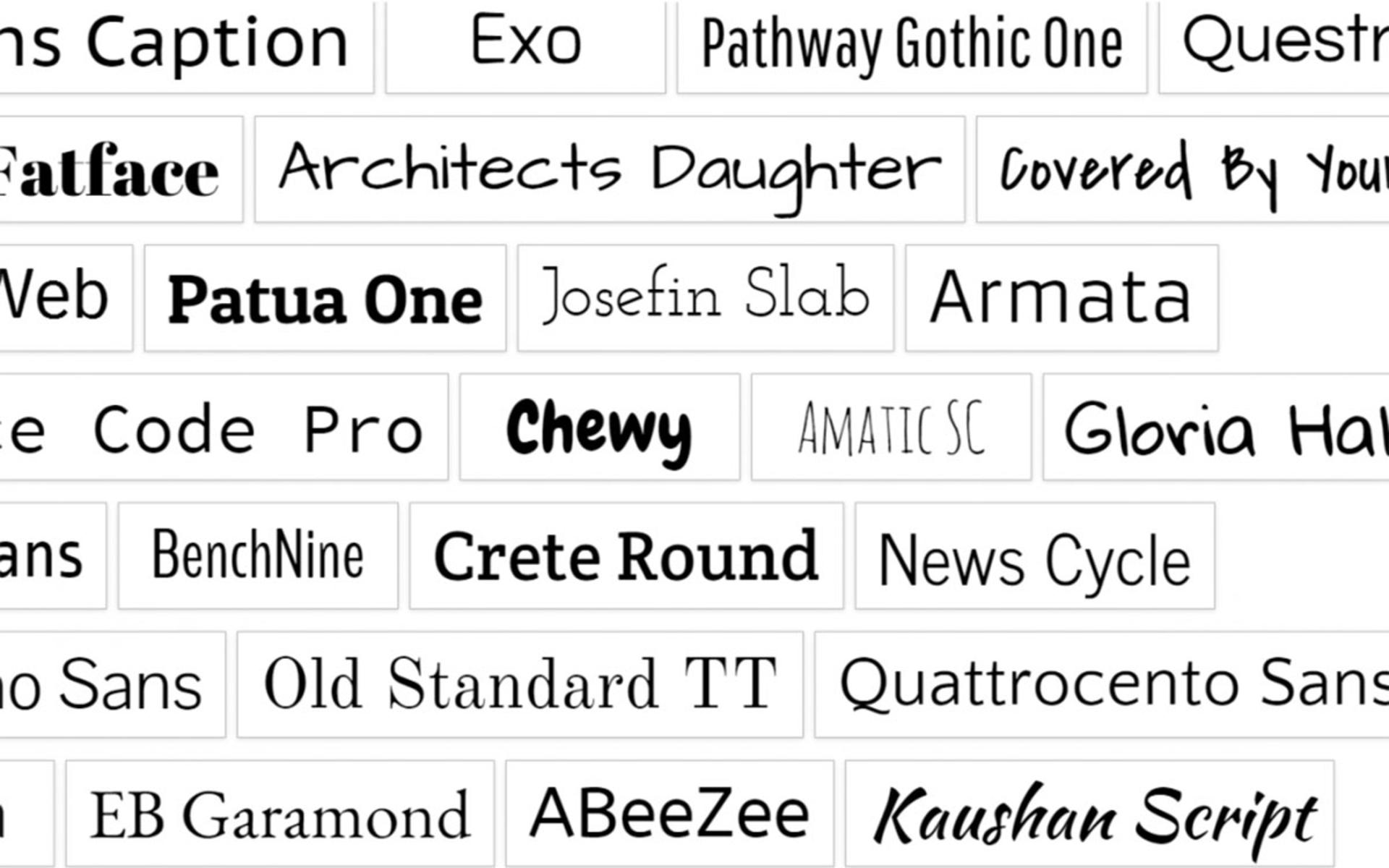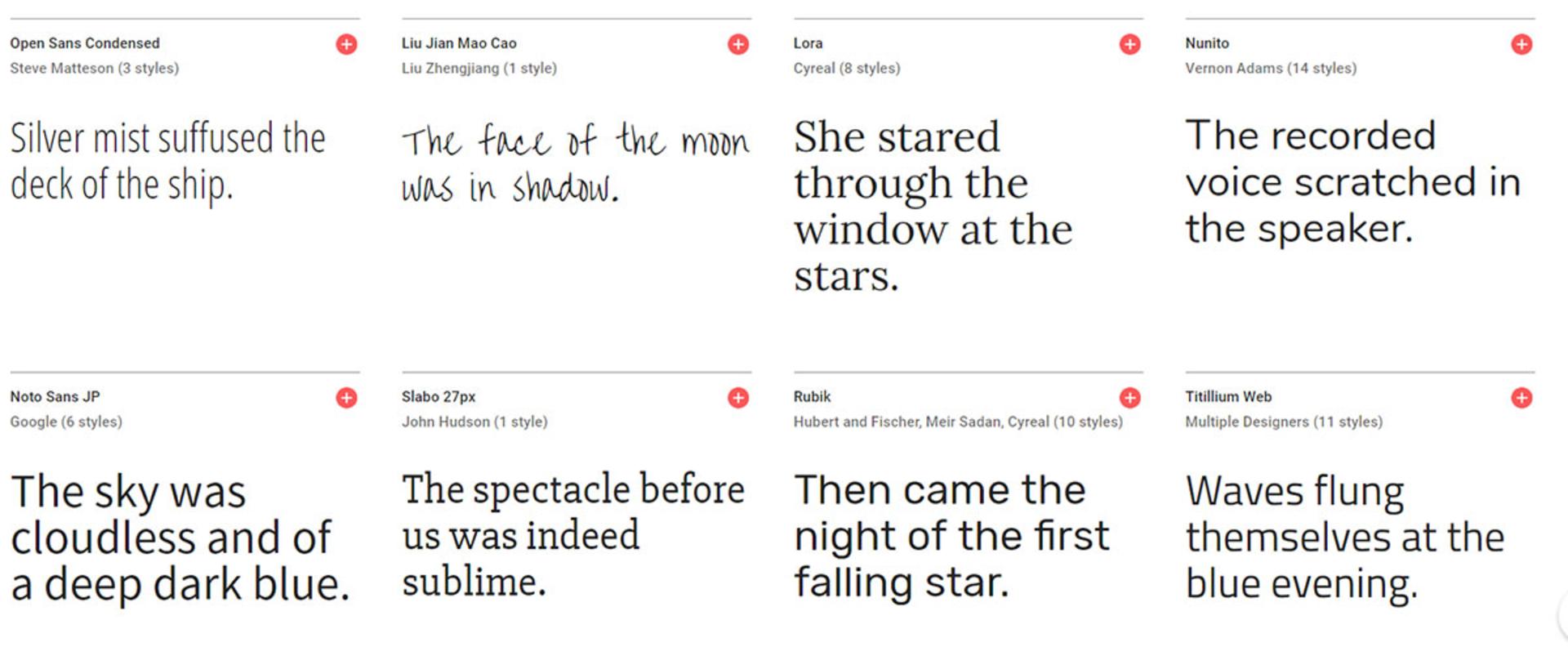
فونت‌های متن‌باز؛ قدمی مثبت در مسیر تشکیل جامعه طراحان خلاق
فونت‌های متن‌باز علاوه بر توزیع آسان و رایگان برای همه‌ی طراحان و علاقه‌مندان، امکان توسعه‌ی بیشتر و بهتر را هم برای این المان‌های گرافیکی فراهم می‌کنند.
فونت‌ها برخی اوقات قیمت‌هایی تا چند صد دلار دارند. درواقع، استفاده از یک خانواده‌ی اختصاصی فونت برای مصارف متنوع تبلیغاتی و تولید محتوا، نیاز به مجوز طراح دارد که در برخی موارد برچسب قیمتی بسیار بالا خواهد داشت. به‌عنوان مثال، فونت Gotham که خصوصا در کمپین‌های انتخاباتی کاربرد دارد، هزینه‌ای نزدیک به هزار دلار به طراحان تحمیل می‌کند و مجوز استفاده از ۶۶ نوع فونت را ارائه می‌کند. ازطرفی سازمان‌هایی وجود دارد که فونت‌ها را به‌صورت رایگان در اختیار علاقه‌مندان قرار می‌دهند. به‌عنوان مثال می‌توان به The League of Moveable Type اشاره کرد که علاوه بر عرضه‌ی رایگان فونت‌ها، آن‌ها را به‌صورت متن‌باز در اختیار طراحان قرار می‌دهد تا بهینه‌سازی و توسعه‌ی نسخه‌های اختصاصی به‌راحتی صورت بگیرد.
فونت Raleway یکی از مشهورترین خانواده‌های متن‌باز در دنیای طراحی فونت محسوب می‌شود. مت مک‌نرنی در سال ۲۰۱۰ این فونت را عرضه کرد که ابتدا تنها در یک حالت در دسترس بود. اکنون ۹ حالت از فونت مذکور در طراحی‌های گوناگون عرضه می‌شود که در سال ۲۰۱۲ به‌کمک پابلو ایمپارلی، رودریگو فونزالیدا و ایگینو مارینی طراحی شدند. اکنون ریل‌وی یکی از محبوب‌ترین فونت‌های مخزن فونت گوگل محسوب می‌شود. مخزن فونت گوگل، مجموعه‌ای از فونت‌های رایگان است که توسط غول موتورهای جست‌وجو، میزبانی می‌شود.
در دهه‌ی گذشته، شرکت‌های متنوع از استارتاپ‌های کوچک همچون Datoo تا غول‌هایی مانند اینتل و IBM با طراحان حرفه‌ای وارد همکاری شدند تا فونت‌هایی را طراحی کرده و سپس به‌صورت متن‌باز عرضه کنند. حتی ادوبی که برخی از فونت‌های خود را با برچسب‌های قیمتی تا چند صد دلار می‌فروشد، خانواده‌ای متن‌باز به‌نام Super Family دارد. تمایل طراحان خصوصا در دنیای وب، به فونت‌های آزاد و متن‌باز به‌راحتی درک می‌شود؛ اما چرا یک طراح فونت مستقل و حرفه‌ای باید اثر خود را به‌صورت متن‌باز ارائه کند؟ پاسخ به این سؤال هم مانند دلیل ارائه‌‌ی نرم‌افزارهای متن‌باز، تنوع زیادی دارد.
تمایل شرکت‌ها برای عرضه‌ی فونت‌های خود به‌صورت متن‌باز، تقریبا شبیه تمایل آن‌ها برای عرضه‌ی نرم‌افزارهای متن‌باز است. به‌عنوان مثال، JetBrains، شرکت ارائه‌‌دهنده‌ی ابزارهای برنامه‌نویسی، فونت جدیدی به‌نام JetBrains Mono برای نوشتن و خواندن کدهای برنامه‌نویسی توسعه داد. آن‌ها سپس فونت مذکور را ازطریق پلتفرم اشتراک کد و همکاری مایکروسافت، گیت‌هاب، به‌صورت متن‌باز عرضه کردند. اکنون برنامه‌نویس‌ها می‌توانند به‌راحتی برای فونت مذکور پیشنهاد ارائه کنند و حتی آن‌ را بهبود دهند. همین دلیلی برای عرضه‌ی نرم‌افزارهای متن‌باز هم صدق می‌کند. شرکت‌ها نرم‌افزار را به‌صورت متن‌باز عرضه می‌کنند تا شاید دیگران در بهبود آن به توسعه‌دهنده‌های اصلی کمک کنند.
حتی اگر طراحان، کمکی به توسعه و بهبود فونت متن‌باز یک شرکت نکنند، باز هم ارائه‌ی فونت به‌صورت متن‌باز برای شرکت‌ها منفعت به‌همراه دارد. به‌عنوان مثال، مدیر ارشد Adobe Type، دان راتیگان می‌گوید عرضه‌ی خانواده‌ی متن‌باز super-family توسط شرکت، امکان بررسی فناوری‌‌های جدید تایپوگرافی همچون «فونت‌های متغیر» را در اختیار آن‌ها قرار داد. فناوری مذکور به طراح اجازه می‌دهد تا وزن فونت را تنظیم کند. آزمایش فناوی با فونت متن‌باز، پیش از ارائه‌ی آن در محصولات دیگر، از مزیت‌های متن‌بازکردن فونت‌ها در ادوبی بوده است.
فونت‌های متن‌باز، به رشد و توسعه‌ی بخش‌های دیگر کسب‌وکار یک شرکت هم کمک می‌کنند. به‌عنوان مثال، مدیر برنامه‌ی مخزن فونت‌های گوگل، دیو کراسلند می‌‌گوید بسیاری از فونت‌هایی که با سرمایه‌گذاری گوگل آماده شدند، مخصوص زبان‌هایی در کشورهای درحال توسعه بودند که پشتیبانی و حمایت کافی را دریافت نمی‌کنند. این رویکردها، در مسیر برنامه‌ی Next Billion Users گوگل قرار می‌گیرند که تلاش می‌کند تا افراد بیشتری را از کشورهای درحال توسعه به دنیای آنلاین بیاورد. پشتیبانی بهتر از زبان‌های بیشتر، یعنی کاربران بیشتر که درنهایت به‌معنای افزایش درآمد گوگل خواهد بود.
انگیزه‌ی عرضه‌ی فونت به‌صورت متن‌باز، همیشه روشن و واضح نیست. در ابتدای سال ۲۰۰۹، یک طراح گرافیک و برنامه‌نویس به‌نام میکا ریچ، سوالی از یک دانشجو را در یک انجمن آنلاین مشاهده کرد که به‌دنبال یادگیری بیشتر درباره‌ی فونت‌ها و نحوه‌ی کار آن‌ها بود. این دانشجو پرسیده بود که آیا فونت باکیفیت متن‌بازی برای یادگیری وجود دارد؟ حدود ۲۰ صفحه پاسخ از طراحان متعدد در آن انجمن منتشر شد که به‌نوعی گفته بودند: «طراحی فونت، مسیر درآمدزایی ما است. چگونه انتظار دارید که اثر خود را رایگان منتشر کنیم؟»
شرکت‌ها با متن‌بازکردن فونت‌ها، روند توسعه‌ی آن‌ها را هم تسهیل می‌کنند
ریچ دلیل پاسخ طراحان فونت را می‌دانست. به‌هرحال طراحی فونت نیاز به تلاش و کار زیادی دارد. علاوه بر کشیدن صدها یا هزارها کاراکتر منحصربه‌فرد، باید ارتباط بین کاراکترها و گروه‌های کاراکتری نیز طراحی شود. ماه‌‌ها زمان با کار طاقت‌فرسا باید انجام شود تا یک فونت به بهره‌برداری برسد. به‌هرحال نیچ با اطلاع از همه‌ی دشواری‌ها، اعتقاد داشت که نباید ایده‌ی متن‌باز را به‌طور کامل کنار گذاشت. او می‌گوید اگر گفتمان متن‌باز وجود نداشت، خودش هیچ‌گاه برنامه‌نویسی نمی‌آموخت. ازطرفی نیچ اعتقاد دارد دنیای برنامه‌نویسی و طراحی تفاوت چندانی با هم ندارند.
تا سال‌های زیاد، تعداد فونت‌های حرفه‌ای متن‌باز با کیفیت بالا، محدود بود. از میان آ‌نها می‌توان Adobe Utopia, Bitstream Charter و Gentium را نام برد. ازطرفی، تعداد فونت‌های بی‌کیفیت رایگان بسیار زیاد بود. بسیاری از آن‌ها تحت مجوز متن‌باز نبودند و درنتیجه طراحان امکان بررسی عمیق‌تر و توسعه و بهبودشان را نداشتند. همین روند باعث می‌شد تا افرادی مانند آن دانشجوی کنجکاو، راه‌حل آسانی برای ورود به دنیای طراحی فونت نداشته باشند. ریچ به‌همراه شریکش کارولین هادیلاکسونو تصمیم گرفت تا مؤسسه‌‌ای برای طراحی و عرضه‌ی فونت‌های متن‌باز و تشویق طراحان برای ارائه‌ی فونت‌های متن‌باز راه‌اندازی کند. آن‌ها در سال ۲۰۰۹ وب‌سایت League of Moveable Type را راه‌اندازی کردند و به‌عنوان اولین نمونه، فونت Junction از خانواده‌ی sans-sarif طراحی‌شده توسط کارولین، منتشر شد.
مانیفست گروه متن‌باز League of Moveable Type، هدف آن‌ها را این‌گونه شرح می‌دهد:
ما نمی‌خواهیم طراحان، از درآمد و سود خود صرف‌نظر کنند. ما از آن‌ها می‌خواهیم تا مزایای ورود به دنیای متن‌باز را درک کنند. مزایایی که نه‌تنها شامل تشکیل جامعه‌ای با استاندارد طراحی حرفه‌ای برای دنیای چاپ و وب می‌شود، بلکه جامعه‌‌ای با قابلیت اشتراک‌گذاری آثار، دانش و تجربه با دیگران و کل جهان را ایجاد می‌کند.
امروزه طراحان مستقل متعددی وجود دارند که فونت‌های جدیدی را بدون انتظار از درآمد، توسعه می‌دهند. به‌عنوان مثال Froyo Tam، خانواده‌ی فونت Ferrite Core SX را ابتدای سال جاری به‌صورت متن‌باز عرضه کرد تا به جریان کنونی بپیوندد. البته او هم مانند بسیرای از طراحان فونت دیگر، فونت‌های پولی هم طراحی می‌کند؛ اما با پیوستن به حرکت متن‌باز، سعی در گسترش فرهنگ این نوع از طراحی داشته است.